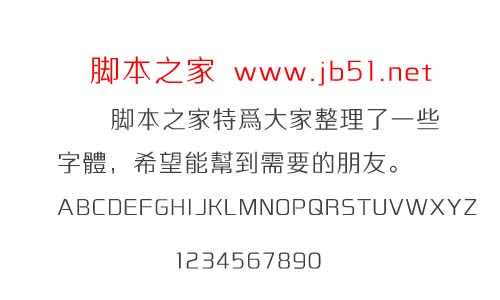
騰祥智黑繁-W1字體是一款用于標題設(shè)計方面的字體,該字體強調(diào)了黑體的特征,筆畫簡潔、硬朗、穩(wěn)重大方,塔形頓點、撇點賦予了智黑特殊的設(shè)計效果,使其既具有黑體的魅力又具有一定的裝飾特色,使黑體具有了靈活、生動的特點,從而形成自己鮮明的特色,可適用于正文、屏顯、設(shè)計類用字,本站提供了騰祥智黑繁-W1字體下載地址,歡迎有喜歡或需要此字體的朋友們前來下載使用。